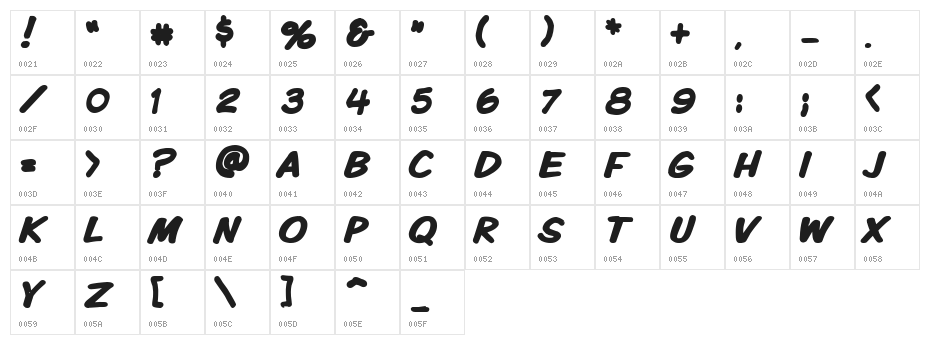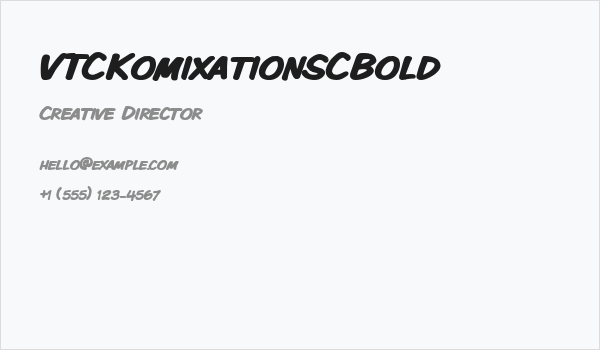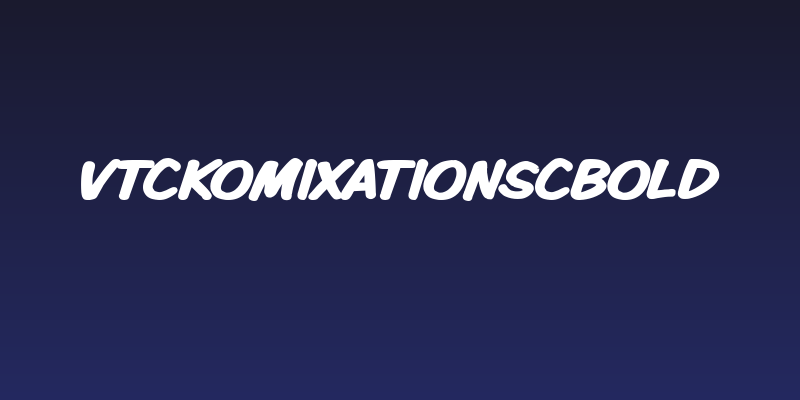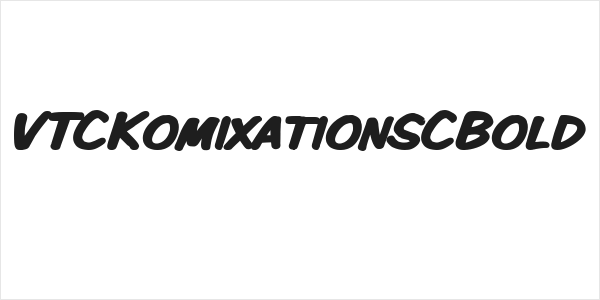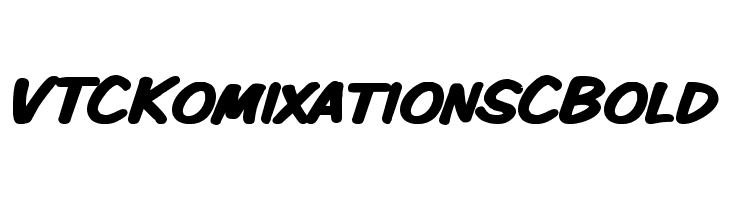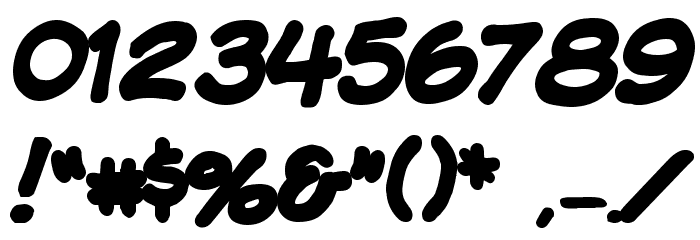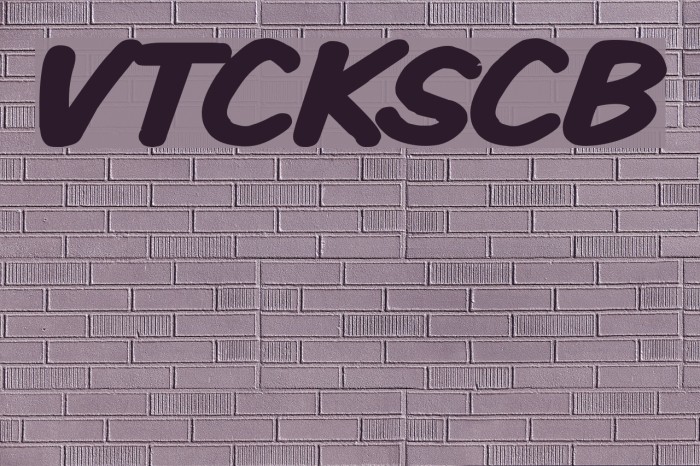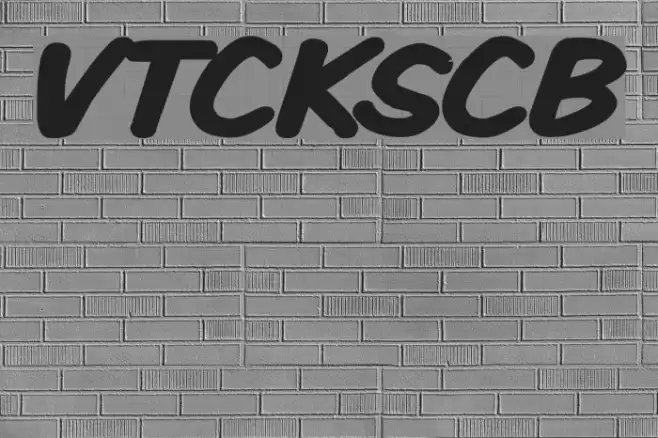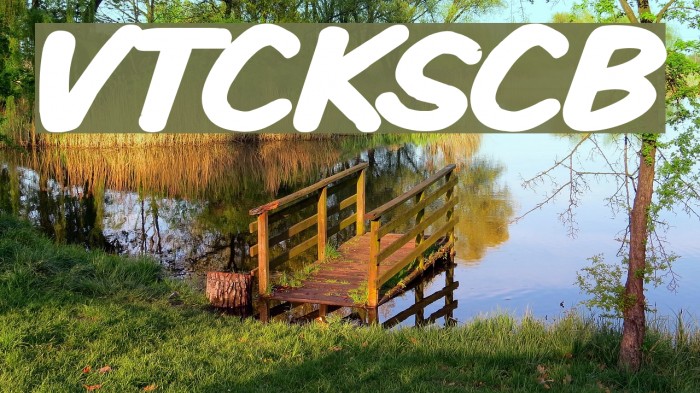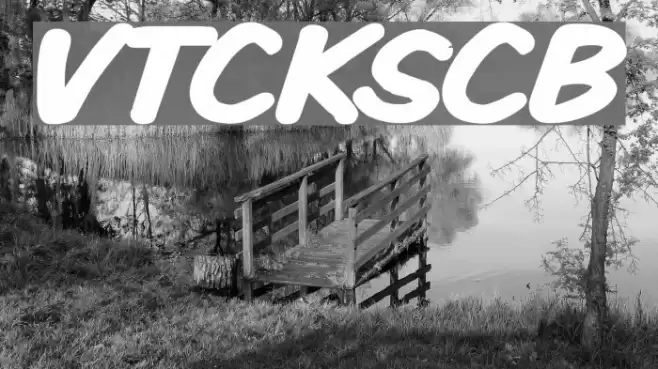
VTCKomixationSCBold Font
✎ Decorative
| النمط العام | Playful, Energetic |
| مشاريع مقترحة | Perfect for comic books, children's books, playful branding, and eye-catching posters. |